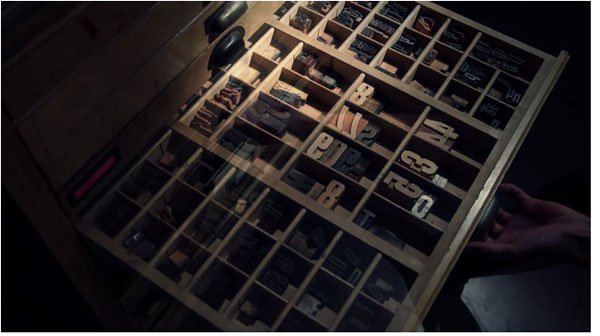
El rescate de las máquinas de tipografía manual
Rescatar el pasado no siempre es cuestión de tiempo. A veces es un trabajo de artesanos. La Universidad de Ciencias Aplicadas de Düsseldorf, en Alemania, quería devolver al presente la tipografía manual. Las letras que se hacen con máquinas pesadas. La habilidad de colocar manualmente las tipos. Las manchas de tinta en los dedos.
Pensaron mezclar tradición y experimento. Querían recuperar un oficio que sucumbe y revolverlo con la estética que domina la actualidad. Fue idea de varios profesores. Jochinke Tobias, Victor Malsy, Uwe Reinhardt y Andreas Uebele. Y, antes de que comenzara el último verano, nacía el taller en esta universidad alemana.
Dos estudiantes de diseño grabaron el proceso en este vídeo que acaban de publicar. “El año pasado nuestra escuela compró una máquina de impresión tipográfica. Necesitaban un videotutorial para enseñar a los alumnos las nociones básicas y para despertarle el interés por esta técnica antigua”, dice Lukas Loss, autor del vídeo junto a Roman Tönjes.
Era su primer tutorial. Y ese debut implicaba para la pareja “un reto interesante”. Sobre todo, “porque era difícil encontrar un equilibrio entre un vídeo instructor y un estilo nuevo, actual, que mostrase lo divertido que resulta trabajar con una máquina extremadamente analógica”.
Loss y Tönjes cogieron una Canon 7D y prepararon una “iluminación básica” en el taller. Grabaron durante dos días. “Roman creó la música en un MPC1000 y después fue añadida a la pieza, de forma rítmica, junto con algunos sonidos reales de la máquina recogidos allí”, añade Loss.
El presente revivió el pasado. Y, además, lo digitalizó.